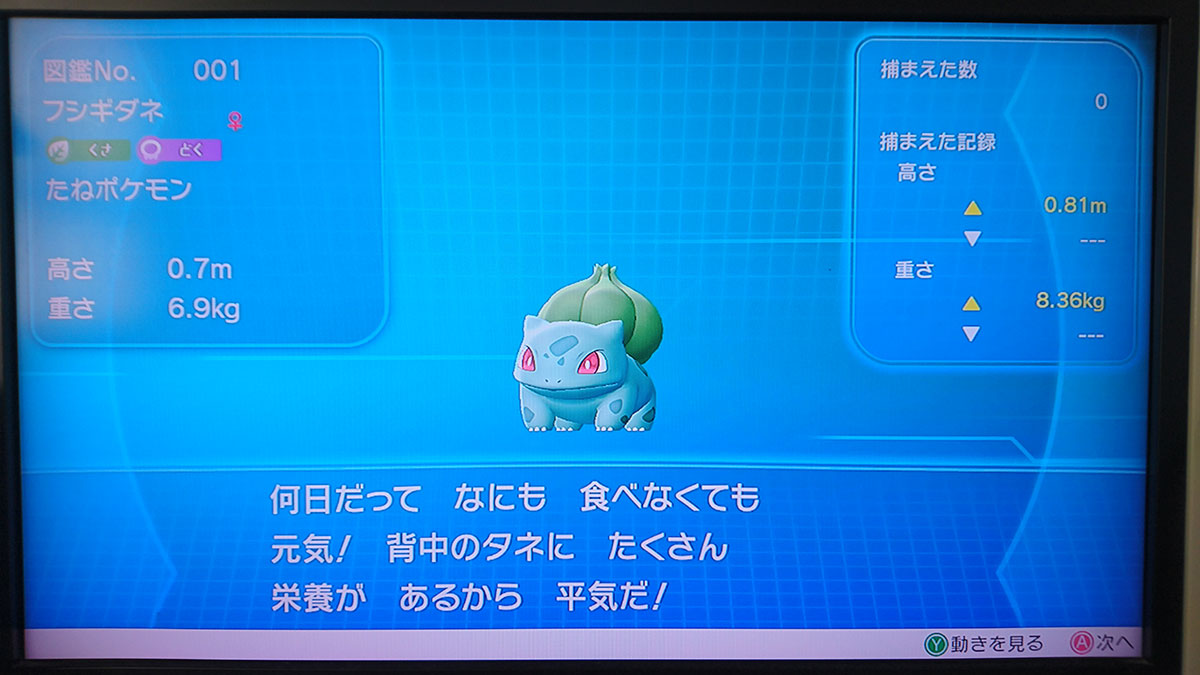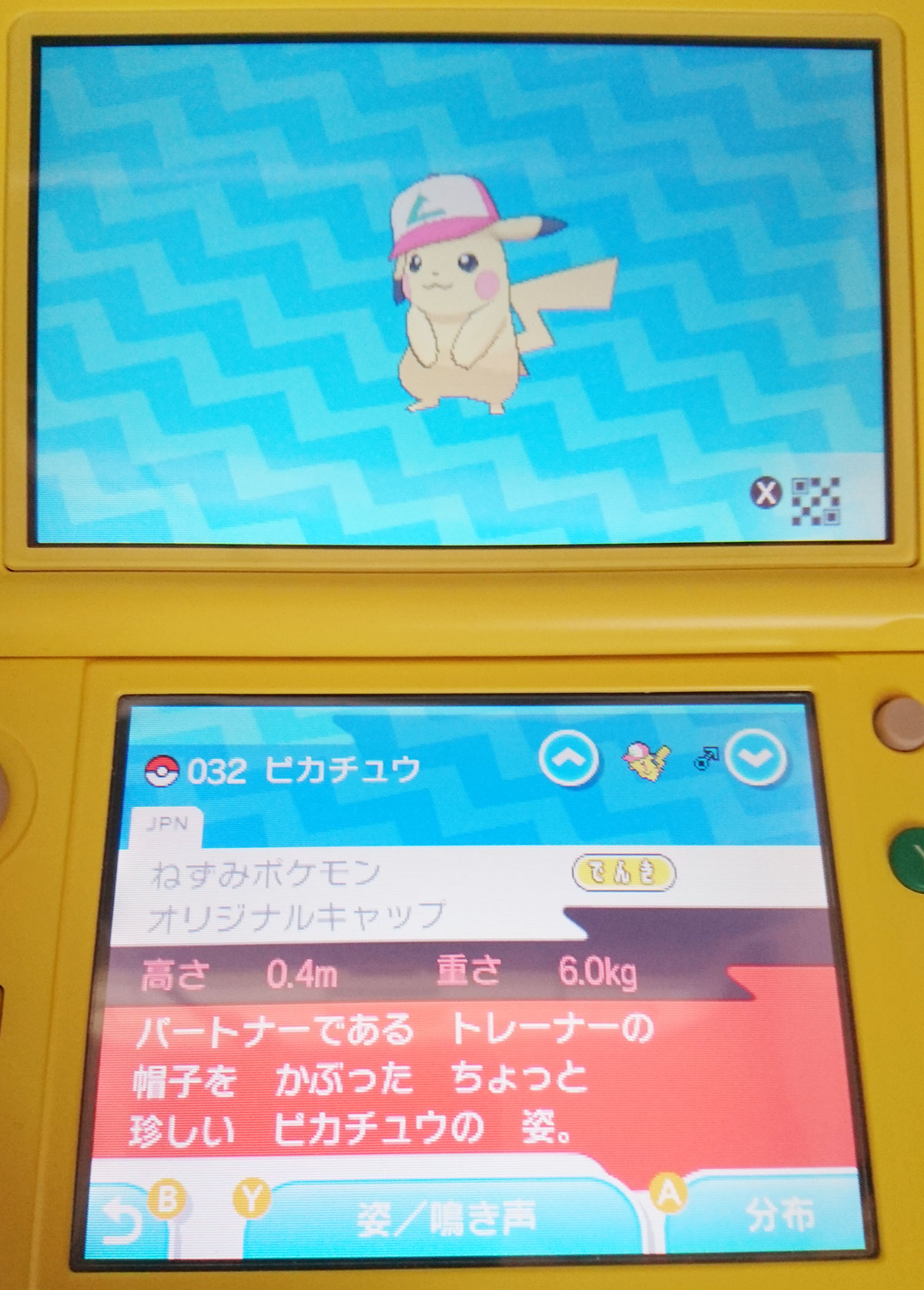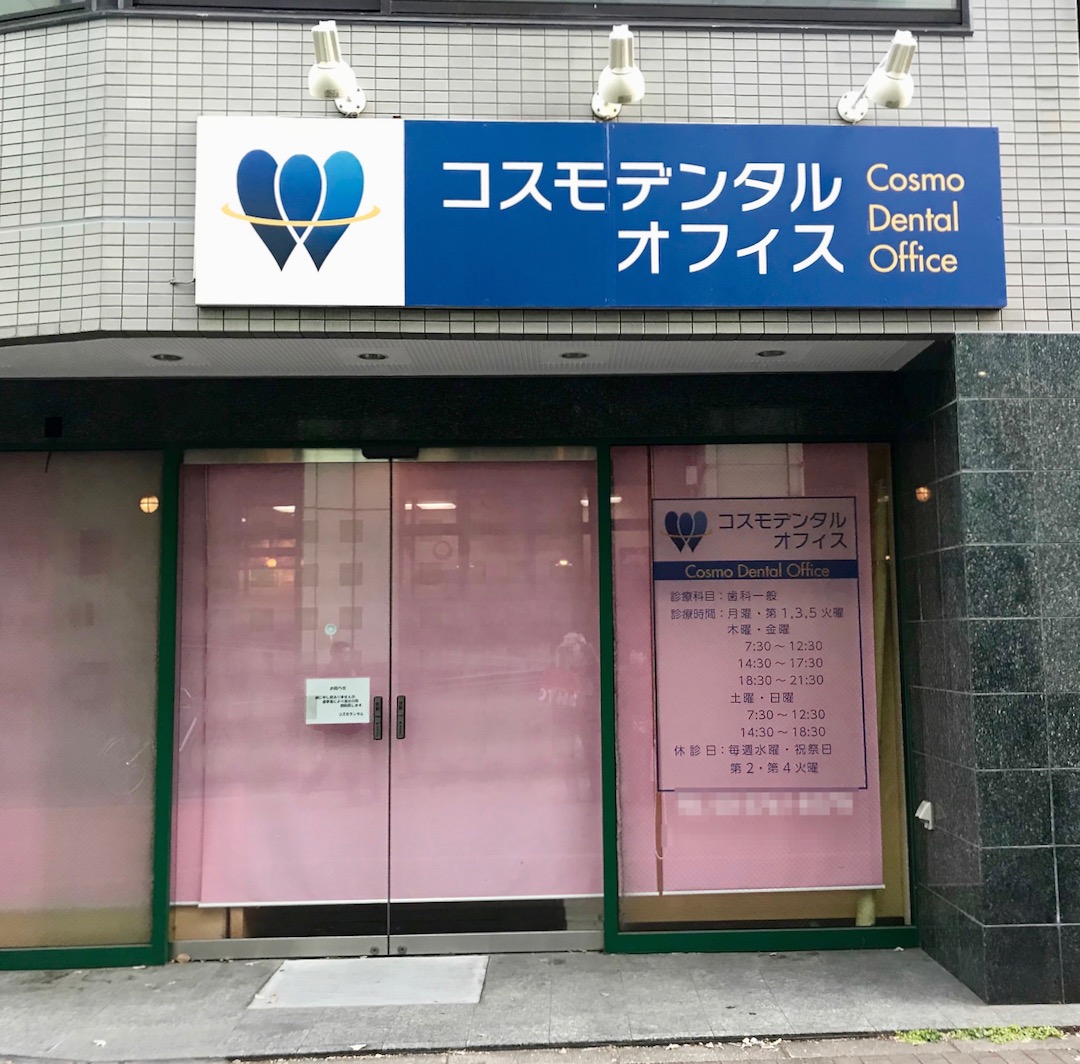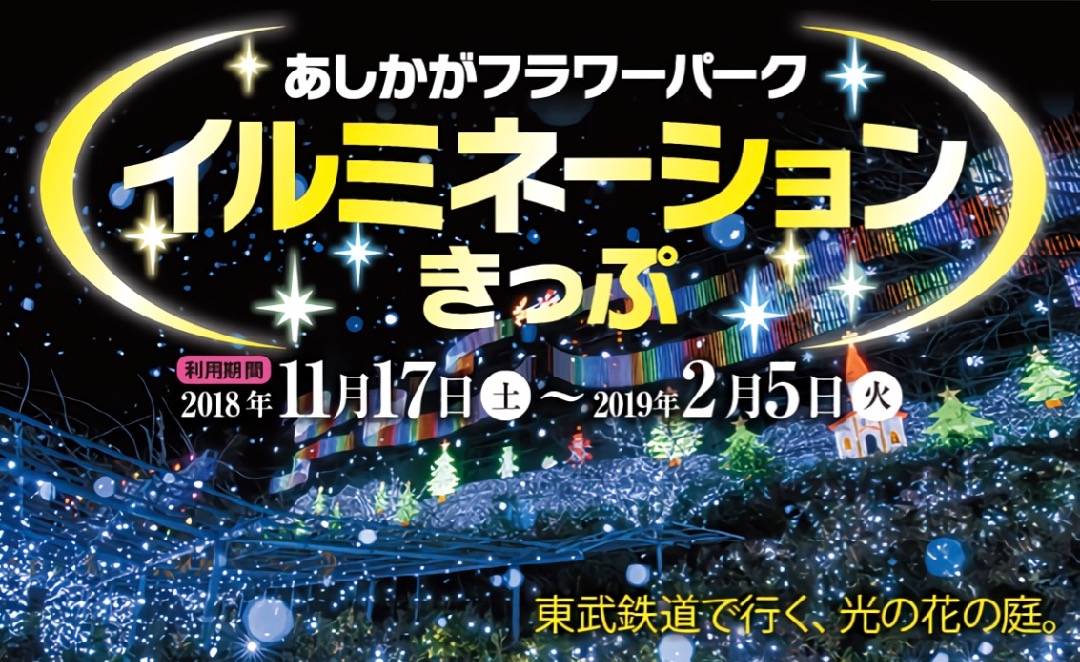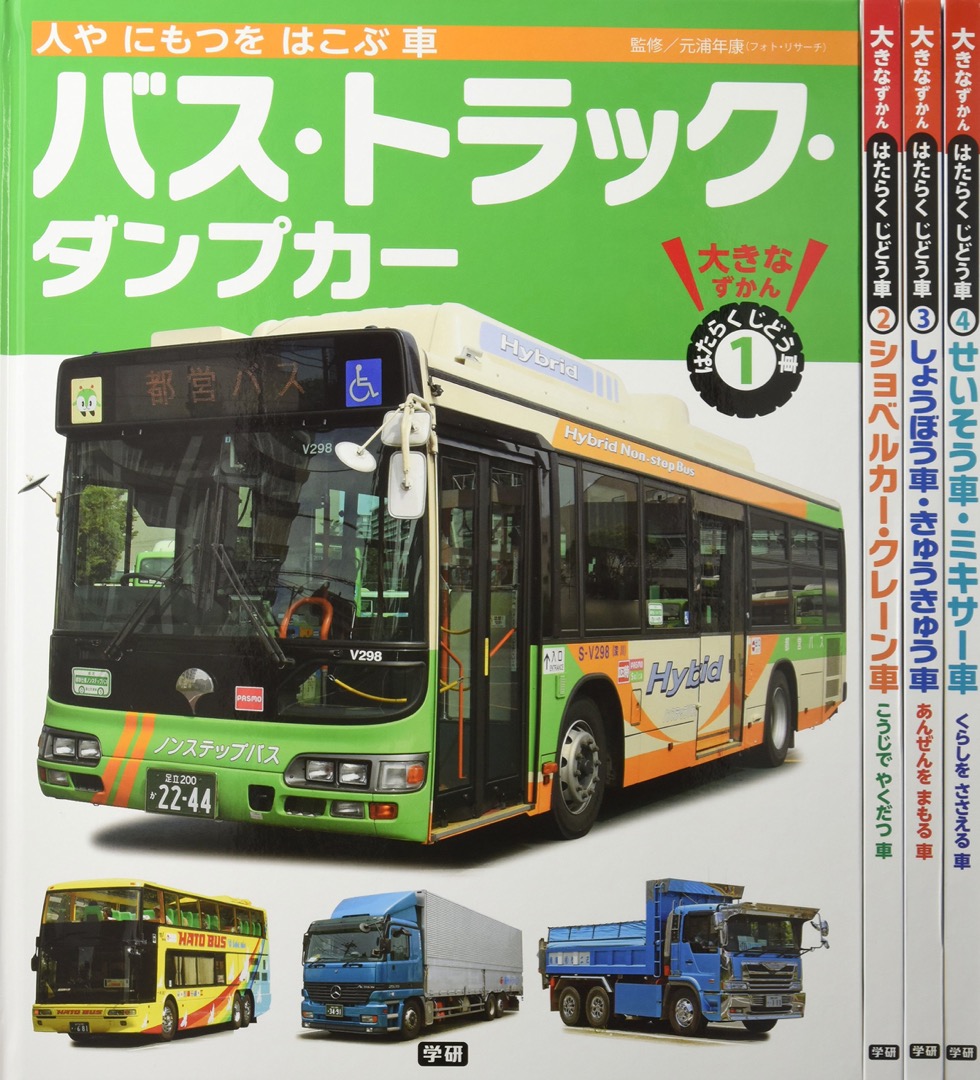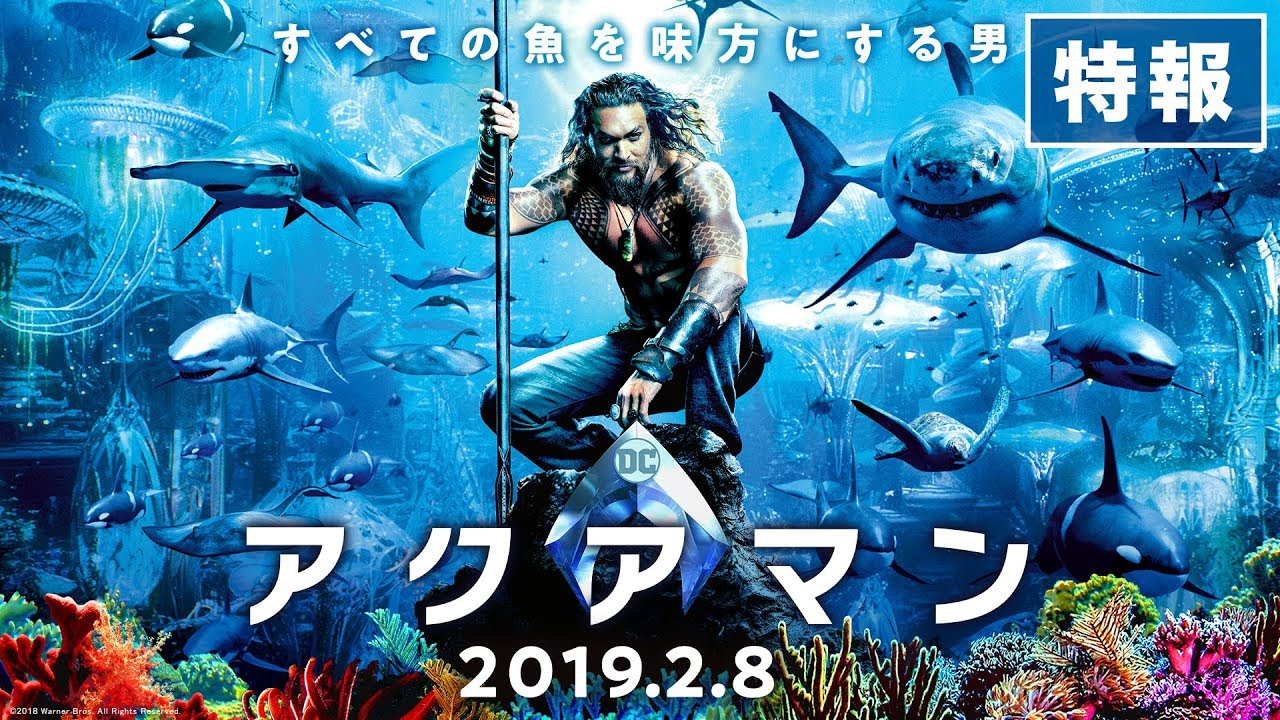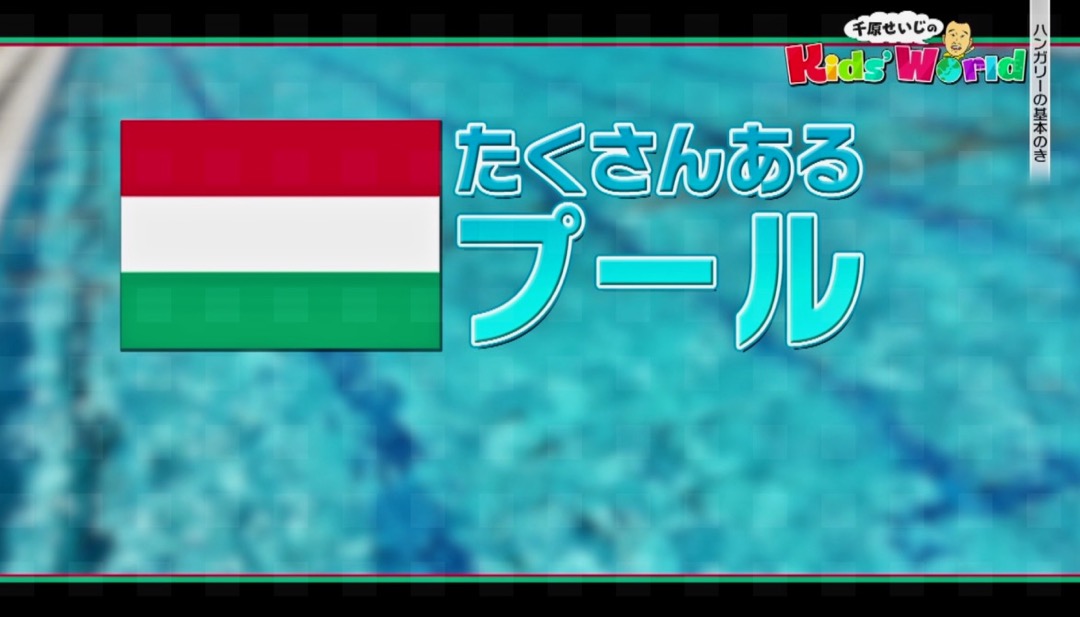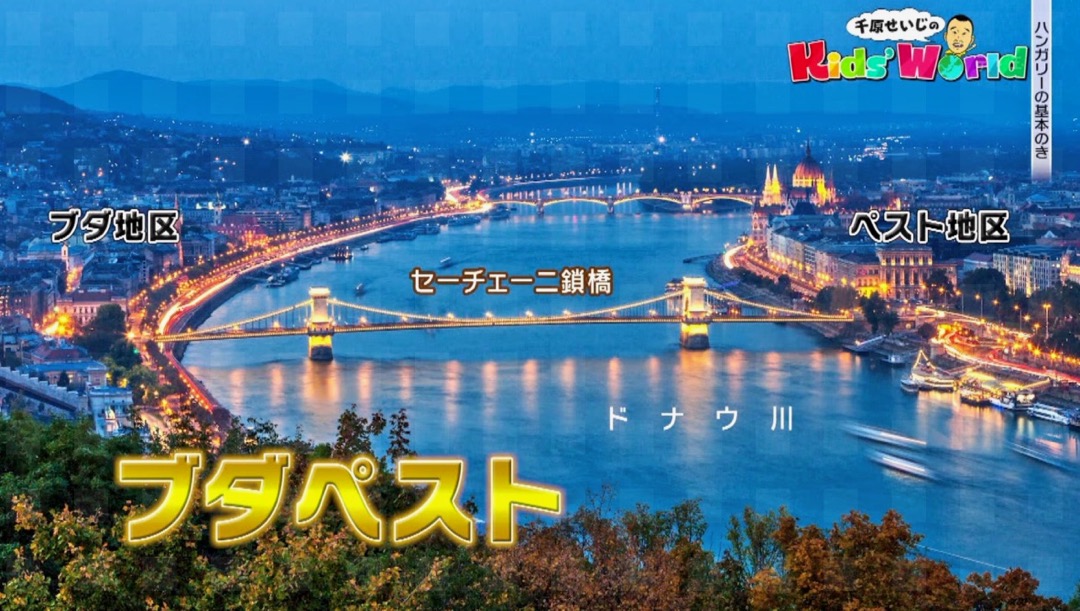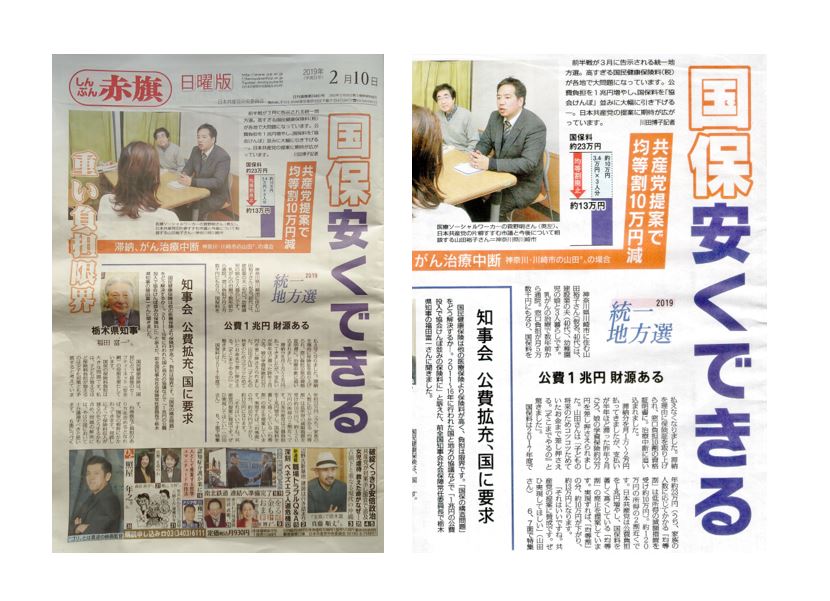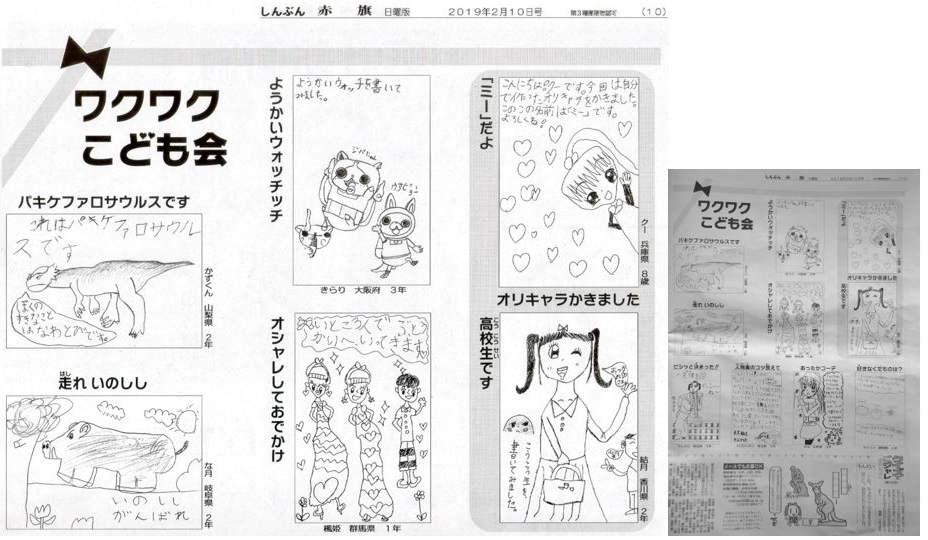
書名:ファミコンコンプリートガイドデラックス
著者:山崎功
発行:主婦の友社
これは、ちょっと古いやつ。
今朝の読売新聞。
マクドナルドは、少年サッカーを応援している。
書名:クロスバイク&ミニベロ最新購入ガイド
発行:コスミック出版
マックで無料券が当たる「メクリマス」キャンペーン。
まじめえひめ。
書名:メガドライブコンプリートガイドwithマーク3
著者:レトロゲーム愛好会
発行:主婦の友社
テレビ東京のローカル路線バス乗り継ぎの旅。
ファイブミニ「調子のいい妄想劇場」 takumi
放映中のCMで「ニタラゴルイカ」書体が使われています。
ちょっと字が小さいですが…。
太さは05辺りでしょうか。
参考にもう1枚。
等幅フォントの「!?」ですね。
私も今朝テレビで見ました。
調子の「調」の字の言べんでニタラゴルイカ確定です。
台所用洗剤。
書名:ビットコイン スタートBook
著者:江嵜 宗利
発行:大蔵財務協会